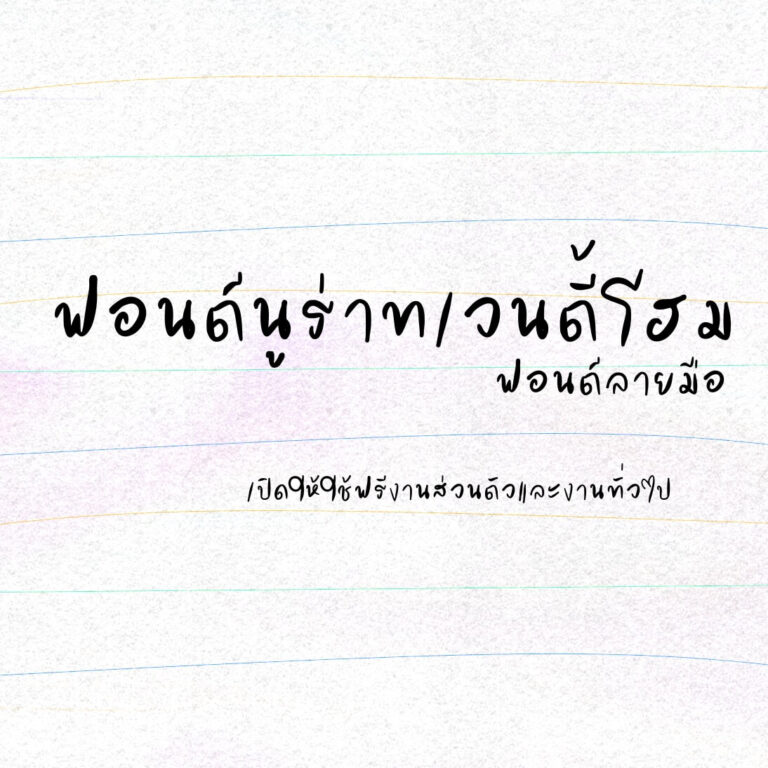
ทอศิลป์ เรียงความ (Torsilp ReiyngKhwam)
การทำอะไรยากๆ สำเร็จสักอย่างพอได้ทำเสร็จก็จะปลื้มๆ หน่อยๆ ตั้งแต่ทำฟอนต์ความฝันอย่างหนึ่งของตัวเองคือ มีฟอนต์พื้นเป็นของตัวเอง แต่ฟอนต์ที่พื้นฐานที่สุด อ่านง่ายที่สุด กลับลงมือทำยากอย่างที่สุด
แจกฟรี ✿ Sleep Font / สลีพ ฟอนต์ ✿ เวอร์ชันทดลองใช้ ฟอนต์รายละเอียดลายมือ 100% ให้โมเมนต์ทำงานส่งอาจารย์ แนวลายมือน่ารักม้ากกก ฟอนต์นี้เป็นฟอนต์แรกที่เปิดแจกแบบทั้งส่วนตัว และเชิงพาณิชย์ หนูแอบตื่นเต้นมากๆ เพราะนั่งเขียนมาหลายวันเลย หวังว่าพี่ๆ ที่โหลดไปใช้จะชอบกันนะคะ♡
ฟอนต์นี้เกิดจากการนำลายมือของครูผู้สอนวิชาสถาปัตยกรรมของข้าพเจ้า มาทำเป็นฟอนต์ไว้ และโอกาสนี้ขอแจกจ่ายเพื่อเป็นอีกหนึ่งแบบอย่างให้กับคนที่หัดฝึกคัดลายมือแบบสถาปัตย์ครับ หรือนำไปใช้ในงานสถาปัตย์ต่างๆ และงานอื่นๆ ทั่วไปตามแต่สะดวกครับ
ฟอนต์ลายมือ เส้นน้ำหนักไม่สม่ำเสมอกัน มีด้วยกัน 3 น้ำหนัก คือ บาง ปกติ หนา นูร่าราดาเปิดให้ใช้ฟรีงานส่วนตัวและงานทั่วไป น้ำหนักบาง
ทอศิลป์ฮงบันจัง (Torsilp Hongbunjug)
หลายสิบปีที่แล้วทำฟอนต์สไตล์ตัวหนังสือแบบเกาหลีไว้ตัวนึง ชื่อ “ทอศิลป์กิมจิ” มาตอนนี้ เอาฟอนต์ตัวนั้นมาทำให้เป็นสไตล์คล้ายลายมือเขียนตามในไตเติลของซีรีส์เกาหลี ทำไปทำมานึกถึงซีรีส์ที่ชอบมากคือ โฮมทาวน์ ชะชะช่า เลยทำต่อจนเสร็จ ใช้ชื่อฟอนต์ว่า “ทอศิลป์ฮงบันจัง”
ฟอนต์ตั้งใจ (TCS4TangJai) ฟอนต์บรัชแบน มีความเรียบร้อย เป็นระเบียบ โหลดฟรีน้ำหนักบาง ใช้ส่วนตัวเท่านั้น
แจกฟรี! 1 น้ำหนัก❤ สำหรับใช้งานส่วนตัว *สามารถนำไปทำคลิปได้ทุกประเภท* ฟอนต์ 6AnnItsara มี 3 ไฟล์ 3 น้ำหนัก ฟอนต์เส้นบรัช มีเท็กซ์เจอร์นิดๆ น่ารัก เก๋ ทันสมัยนิยม จะใช้เป็นหัวข้อ หรือจะเป็นรายละเอียดเยอะๆ ก็ยังเอาอยู่ค่ะ ฝากเอ็นดูน้องด้วยค่า
ฟอนต์กอหญ้า (TCS4Koya) เป็นฟอนต์เส้นไม่เรียบ มีความหยัก โหลดฟรีน้ำหนักบาง ใช้ส่วนตัวเท่านั้น